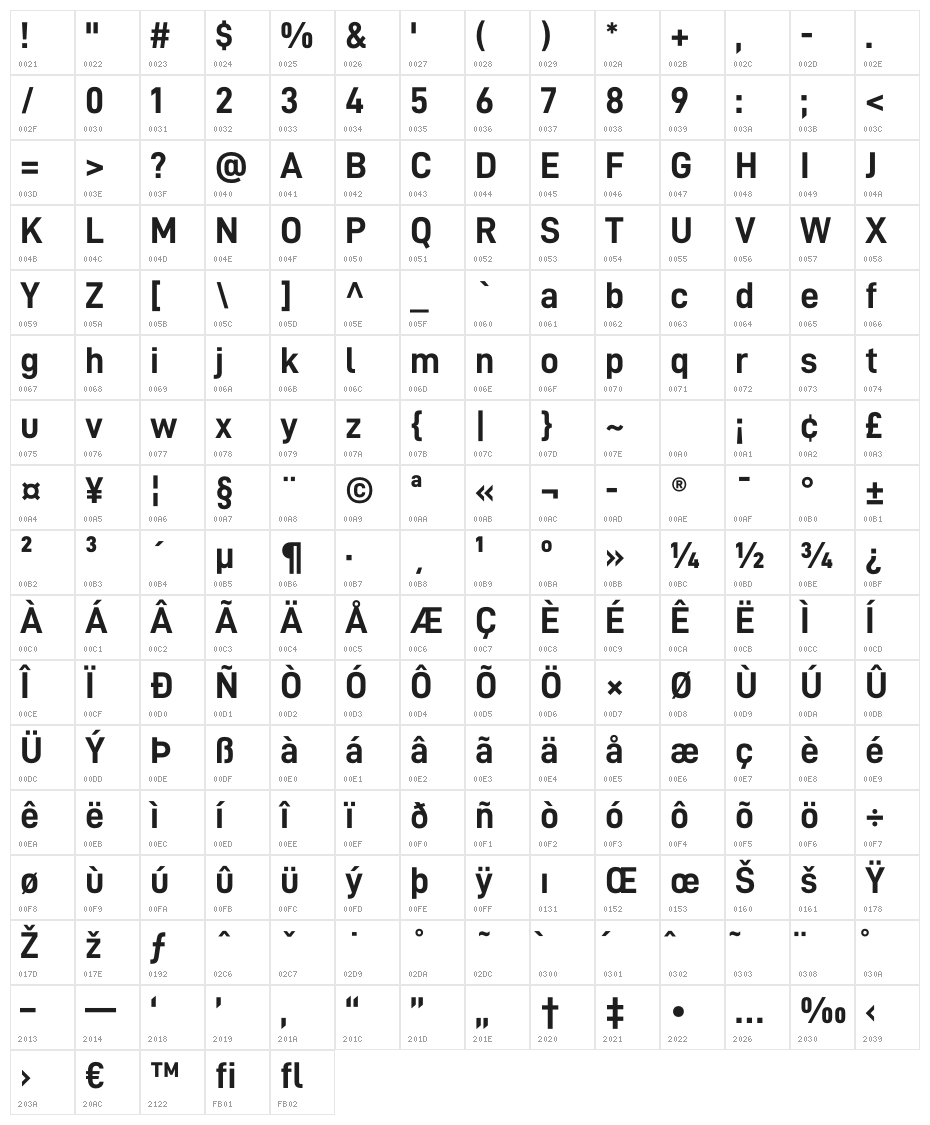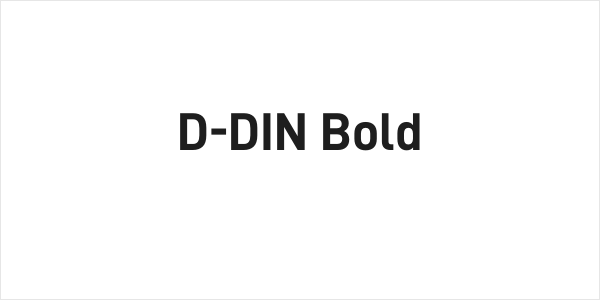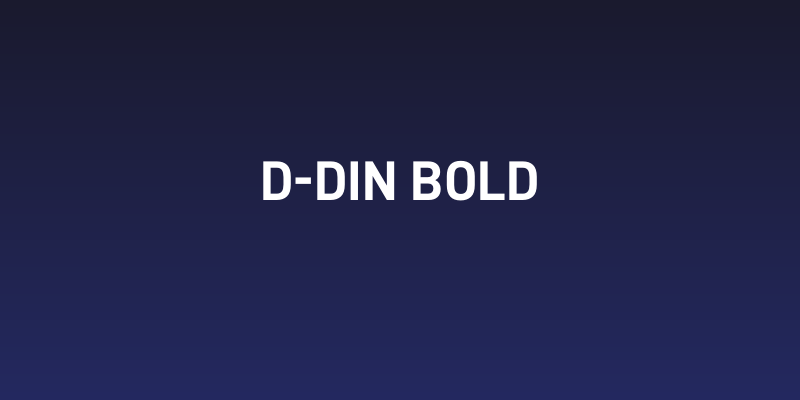
D-DIN Bold Font
| Anwendungsfall | Headlines, Body text, Logos |
| Vorgeschlagene Projekte | Ideal for corporate branding, signage, user interfaces, and editorial design where clarity and professionalism are key. |